So beschriften Sie Bilder in der Game of Thrones-Schriftart auf iOS
Die Fernsehserie "Game of Thrones" hat sich einen Platz in der Geschichte gesichert, sowohl als eine der beliebtesten Sendungen aller Zeiten als auch als eine der am häufigsten illegal heruntergeladenen. Die Serie besticht durch ihre facettenreichen Charaktere und unvergesslichen Zitate, die sich hervorragend für Bildunterschriften eignen. Doch nicht nur der Dialog, auch die Schriftart der Serie erfreut sich großer Beliebtheit und steht der von "Harry Potter" und "Der Herr der Ringe" in nichts nach. Wer seine iPhone-Fotos mit Text in dieser markanten Schrift versehen möchte, kann dies ganz einfach mit der App "Game of Fonts" tun.
Die "Game of Thrones"-Schriftart auf dem Smartphone
"Game of Fonts" ist eine kostenlose App, die im App Store erhältlich ist. Nach dem Start der App können Nutzer über die Schaltflächen am unteren Rand ein Bild oder Video auswählen, das sie mit einer Beschriftung und einem Rahmen versehen möchten.
Zunächst wird das gewünschte Bild oder Video importiert. Anschließend kann die Schriftart (erste Schaltfläche von links) oder ein Rahmen (dritte Schaltfläche von links) hinzugefügt werden.
Die App bietet die authentische Schriftart und passende Rahmen im Stil der Serie, wobei die Auswahl allerdings begrenzt ist. Die Schriftgröße ist veränderbar, jedoch ist die kleinste Einstellung noch immer relativ groß. Es stehen drei Rahmen zur Auswahl: der Eiserne Thron, ein Flammen- und ein Eisrahmen. Die Schriftart selbst ist in den gleichen Varianten verfügbar, und neben der Größe lässt sich auch die Textausrichtung verändern.
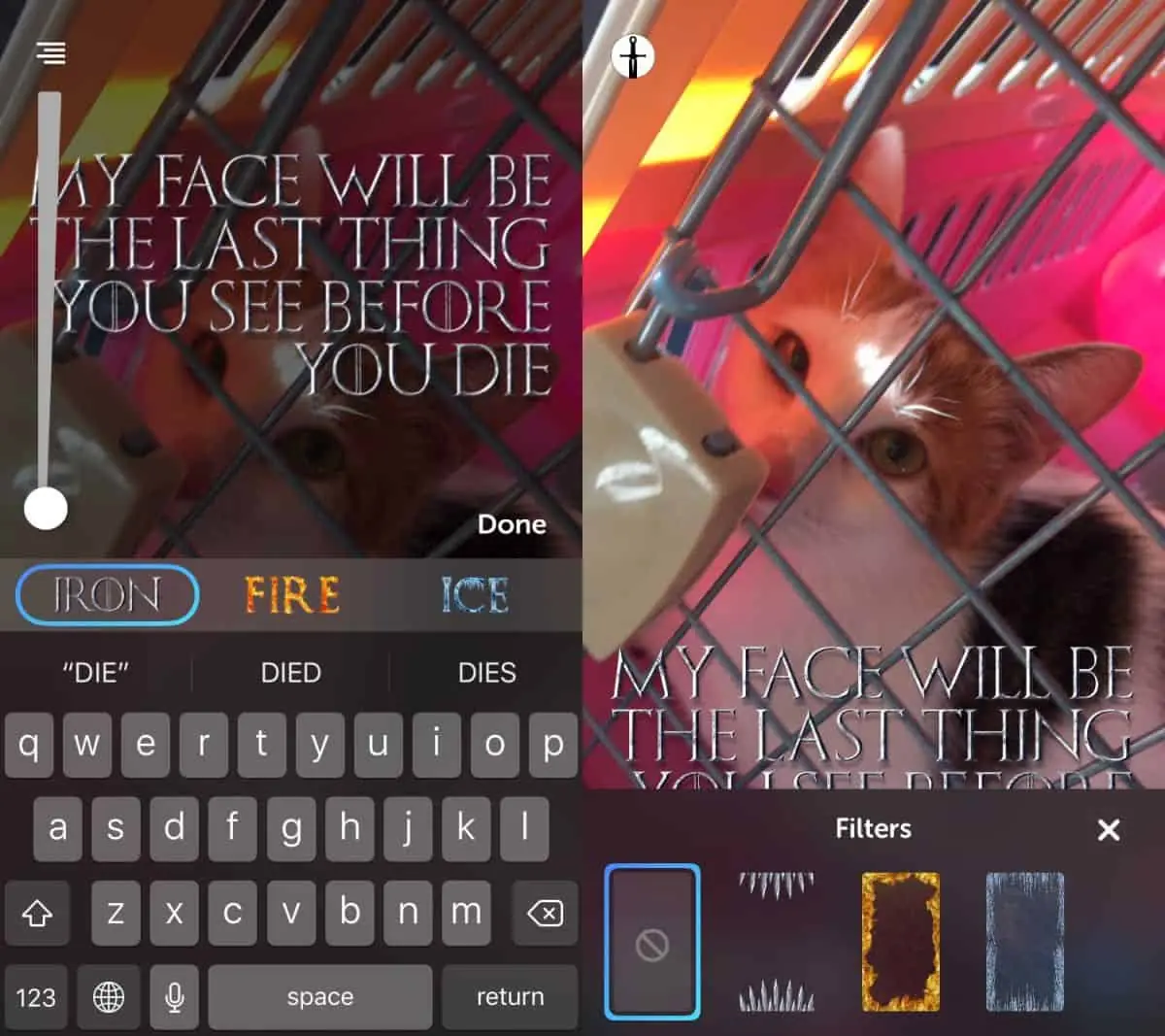
Mit dem Ende von "Game of Thrones" haben Apps wie diese immer mehr an Bedeutung gewonnen. Auch andere Social-Media-Anwendungen haben spezielle Filter im Stil der Serie eingeführt. Snapchat bot sogar ein spezielles Geo-Filter-Objektiv an, das allerdings nur in New York funktionierte und möglicherweise bereits abgelaufen ist.
Der entscheidende Faktor ist die Auswahl eines passenden Bildes. Nicht alle Bilder eignen sich optimal für das Lesen in dieser Schriftart. Für dunklere Bilder empfiehlt sich der Eiserne Thron oder die Eis-Schrift mit passendem Rahmen. Bei helleren Bildern ist die Flammen-Version wahrscheinlich am besten lesbar. Wer die Schriftart der App in Kombination mit anderen Social-Media-Apps nutzen möchte, sollte das Bild zuerst in der gewünschten App erstellen und in der eigenen Galerie speichern, bevor es in "Game of Fonts" importiert und beschriftet wird.